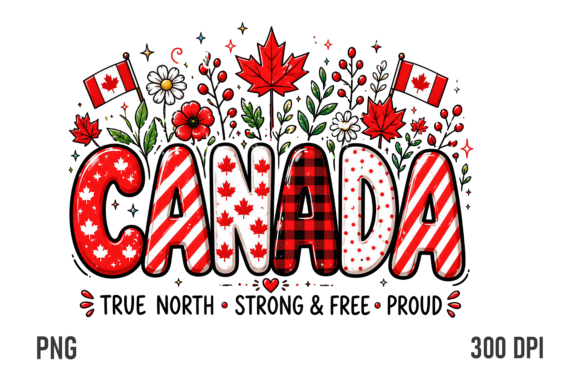
Canada Floral Patriotic Letter PNG
หากคุณกำลังมองหาเนื้อหาคุณภาพสูงเช่น Canada Floral Patriotic Letter PNG แพ็คเกจพรีเมียมนี้เป็นตัวเลือกที่ยอดเยี่ยมสำหรับโปรเจ็กต์สร้างสรรค์ของคุณ
สร้างขึ้นอย่างแม่นยำ Canada Floral Patriotic Letter PNG ให้เวกเตอร์ที่สะอาด พิมพ์ตัวอักษรที่ราบรื่น และใบอนุญาตเชิงพาณิชย์เพื่อความสบายใจ
ไม่ว่าคุณจะสร้างผลิตภัณฑ์ POD (Print on Demand) คำเชิญงานแต่งงาน หรือกราฟิกโซเชียลมีเดีย Canada Floral Patriotic Letter PNG ก็เหมาะสมอย่างยิ่ง